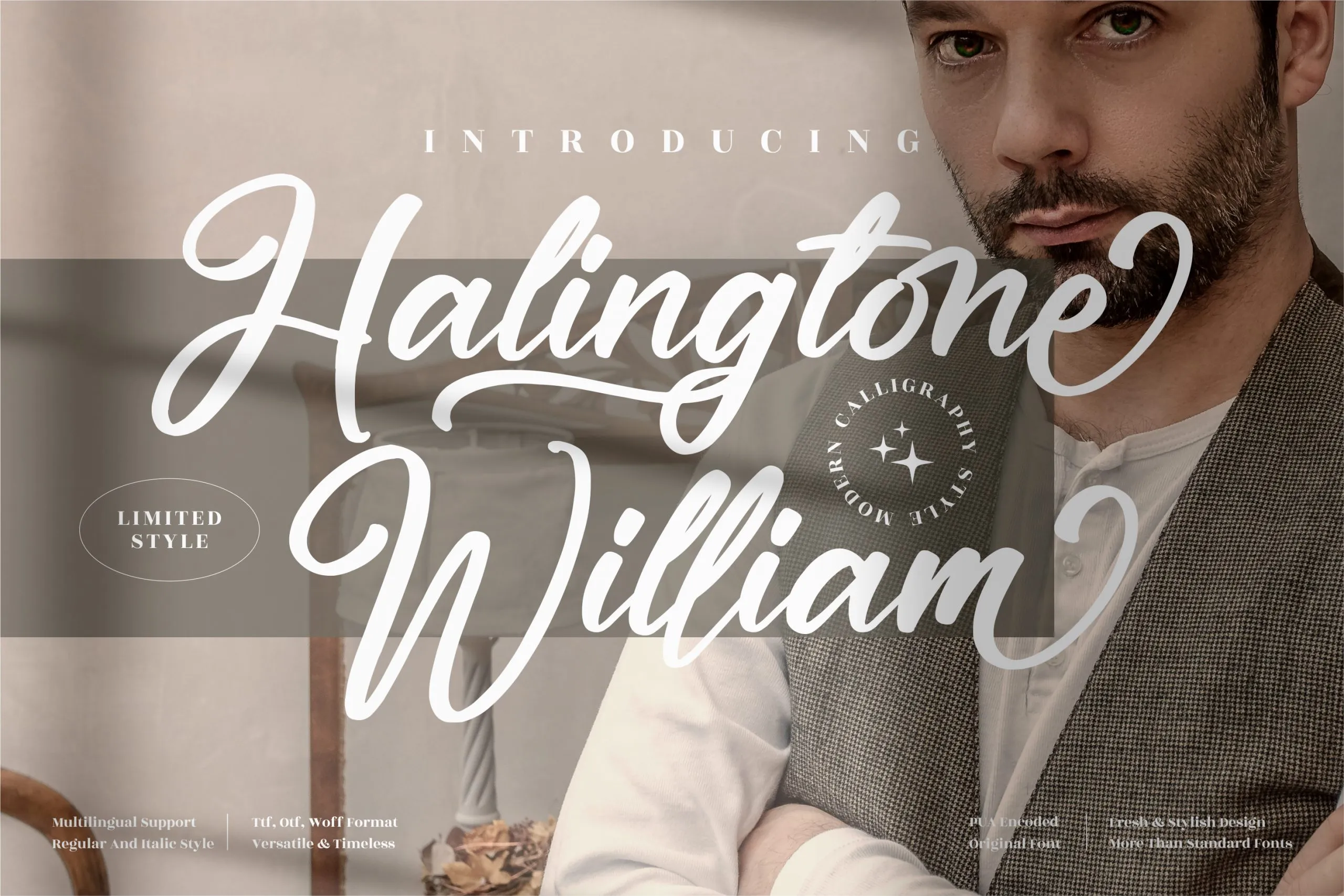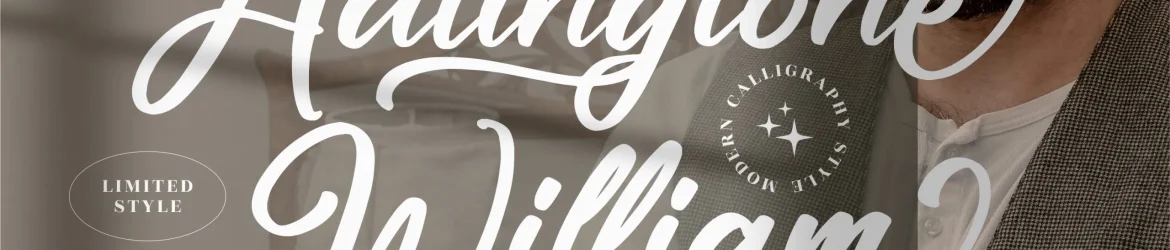
A Halingtone William Font é uma elegante escolha para qualquer projeto que busque qualidade premium e personalização. Oferecida pelo estúdio Perspectype Studio, esta é uma fonte de assinatura de alto nível adequada para criar logos, projetos de marca, designs de móveis de casa, embalagens de produtos, tigelas, cartões de mensagens, cartões de convite, adesivos e até mesmo etiquetas. Ideal tanto para itens básicos quanto luxuosos, a fonte Halingtone William oferece um toque sofisticado em sua aplicação, garantindo que seu trabalho atinja o nível desejado de sofisticação. É uma escolha perfeita para qualquer projeto onde uma assinatura de alta qualidade é necessária, seja para adicionar o seu toque pessoal ou para projetos com padrões exclusivos e impecáveis.